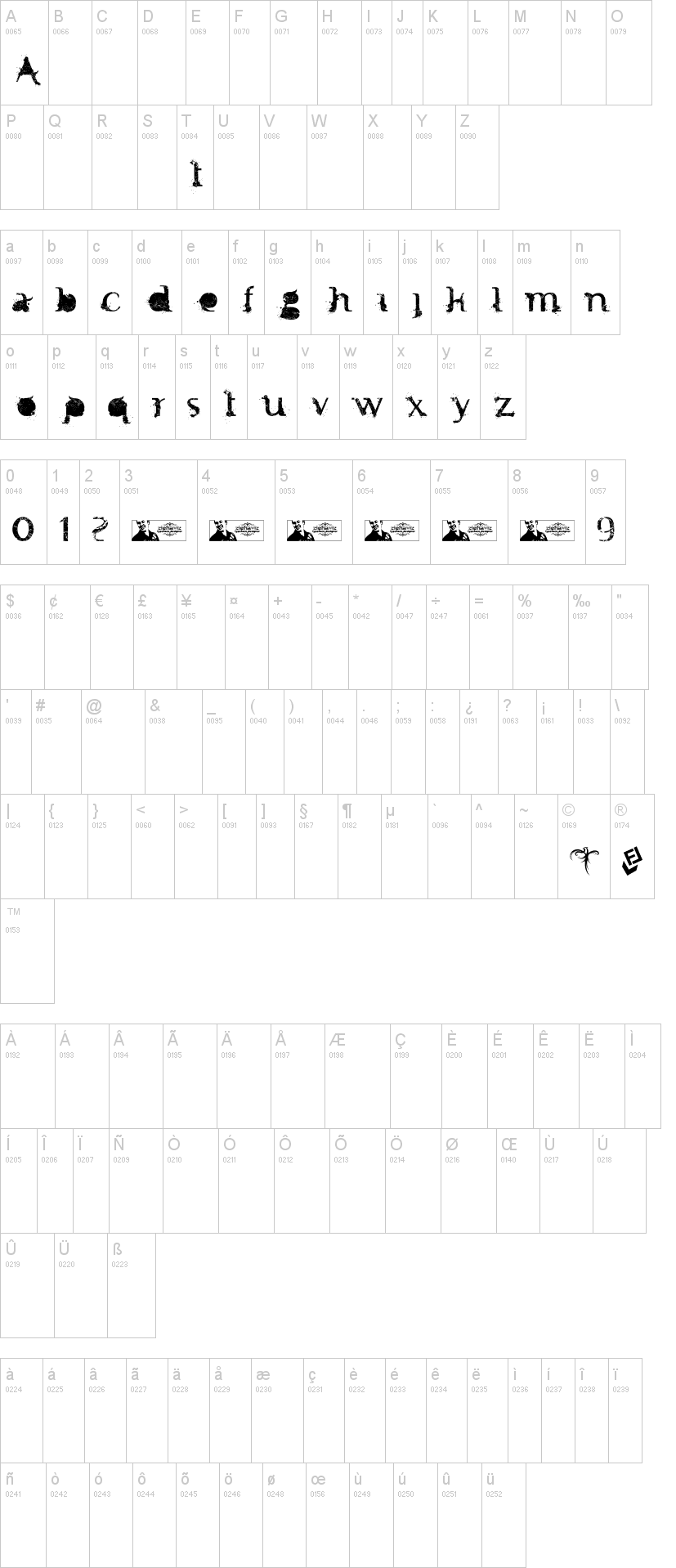
Note of the authorFTF Minthee Indonesiana 3th
-INDONESIA-
Suatu kebanggaan bagi Fizz-Labz dan FTF merangkai huruf ini menjadi alfabet utuh dari a-z "lowerchase"